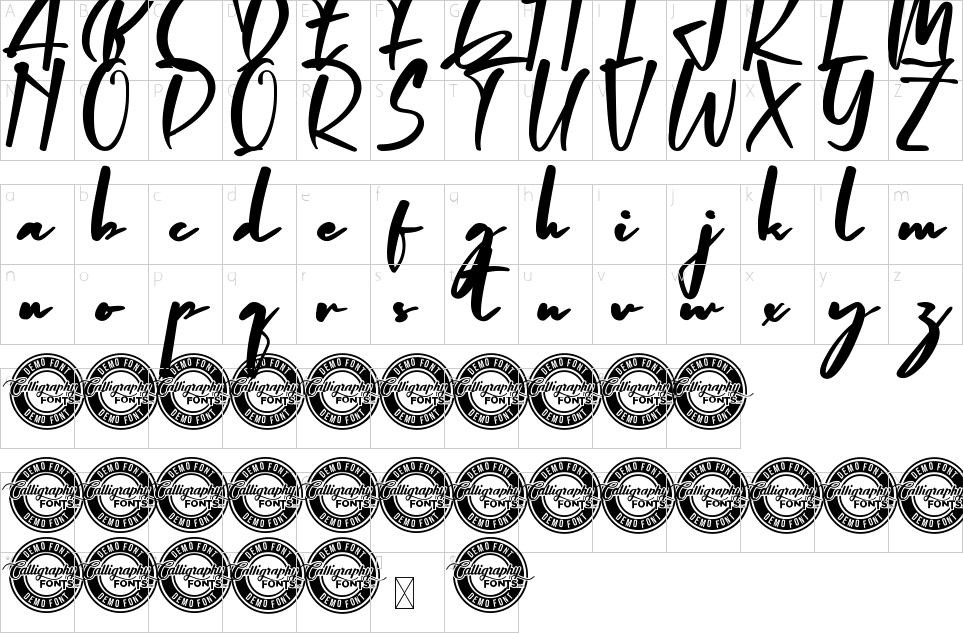
A fonte ‘Authentic Genious’ é uma criação cuidadosamente pensada para aqueles que buscam um efeito elegante e sofisticado em seus projetos digitais. Desenvolvida por CalligraphyFonts, esta fonte vem em versões compatíveis com Windows e Mac, proporcionando uma experiência sem erros em diversos ambientes de trabalho. Com seu design refinado e perfeitamente balanceado, ‘Authentic Genious’ é perfeito para criar textos que transmitem seriedade e confiança, tornando-se um recurso valioso para designers, profissionais de marketing e desenvolvedores de software. Com mais de 1.022 downloads, a qualidade e a relevância de ‘Authentic Genious’ são reconhecidas e valorizadas por designers de todo o mundo, tornando-a uma fonte grata para explorar.